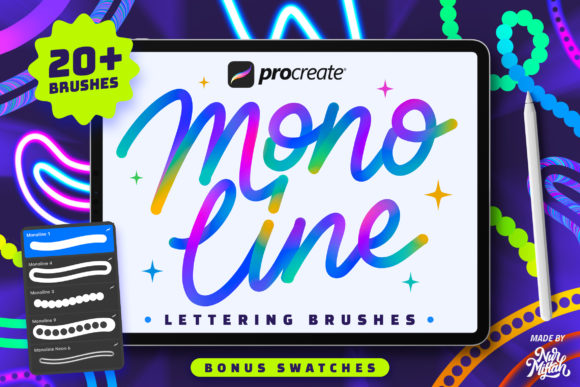
Procreate Monoline Lettering Brushes
Если вы ищете высококачественные ресурсы, такие как Procreate Monoline Lettering Brushes, этот премиум-пакет — фантастический выбор для ваших творческих проектов.
Созданный с высокой точностью, Procreate Monoline Lettering Brushes предоставляет чистые векторы, плавную типографику и коммерческую лицензию для вашего спокойствия.
Создаете ли вы продукты POD (печать по требованию), свадебные приглашения или графику для социальных сетей, Procreate Monoline Lettering Brushes станет идеальным выбором.